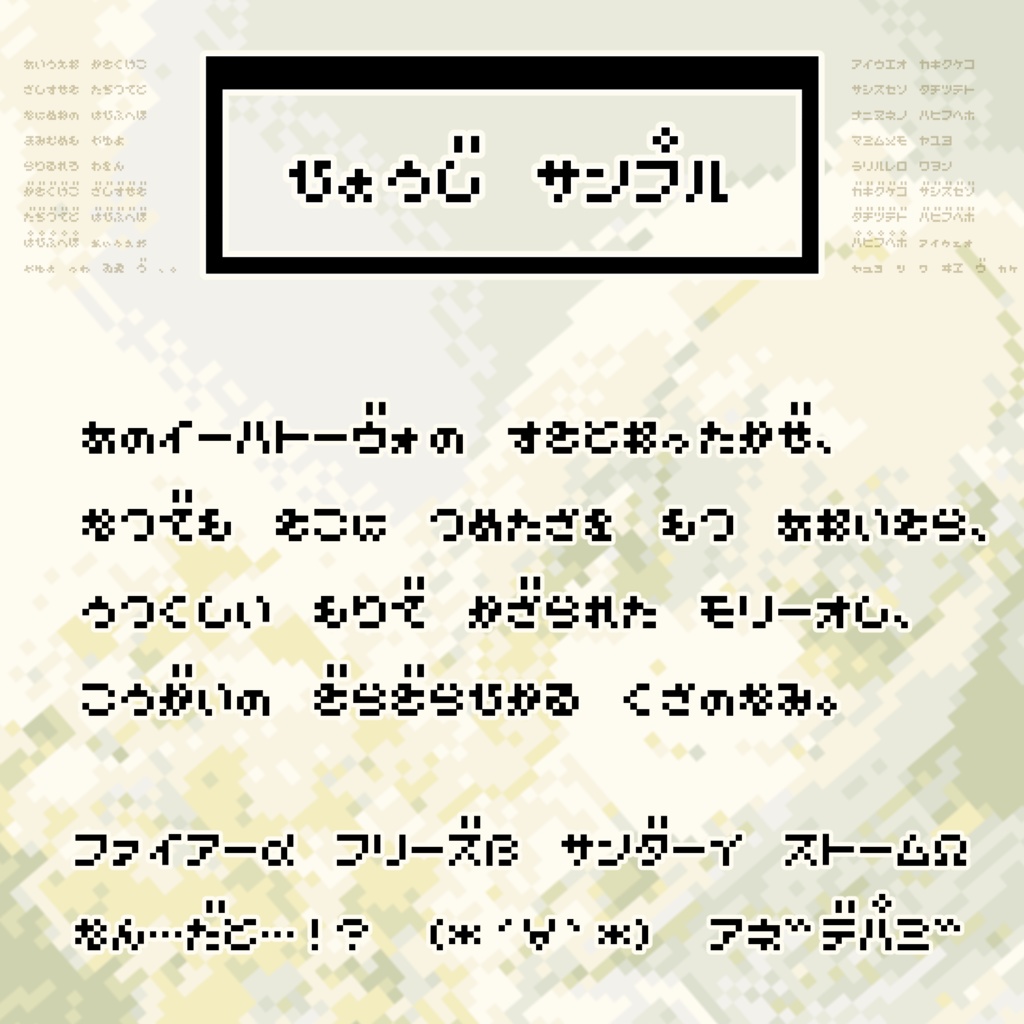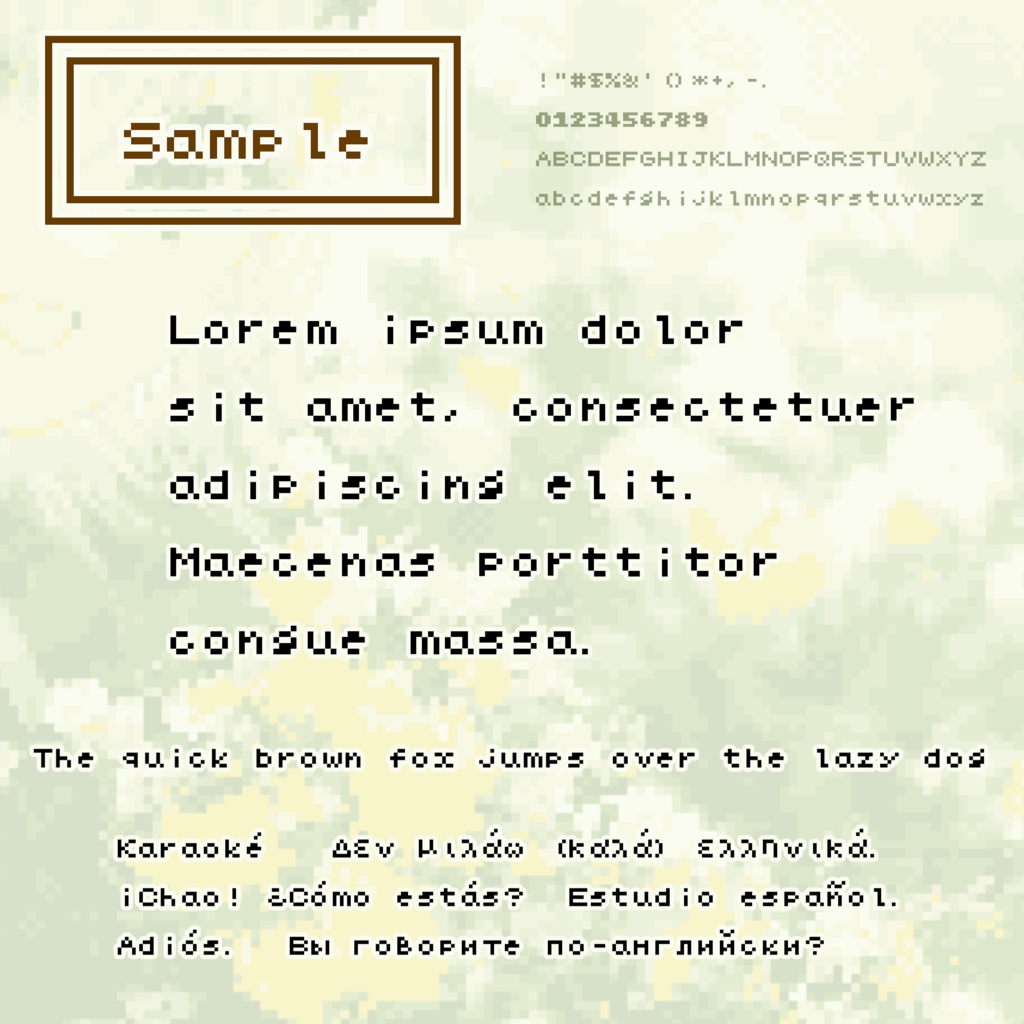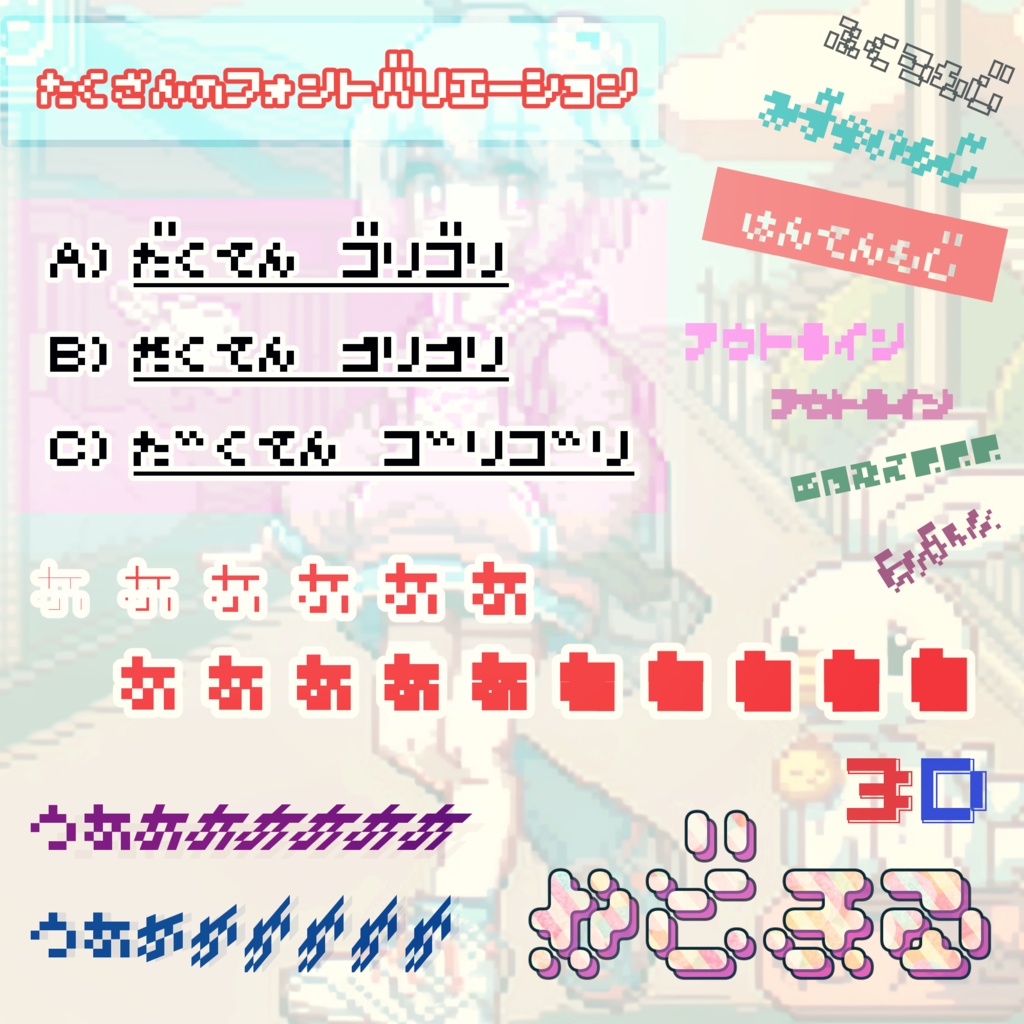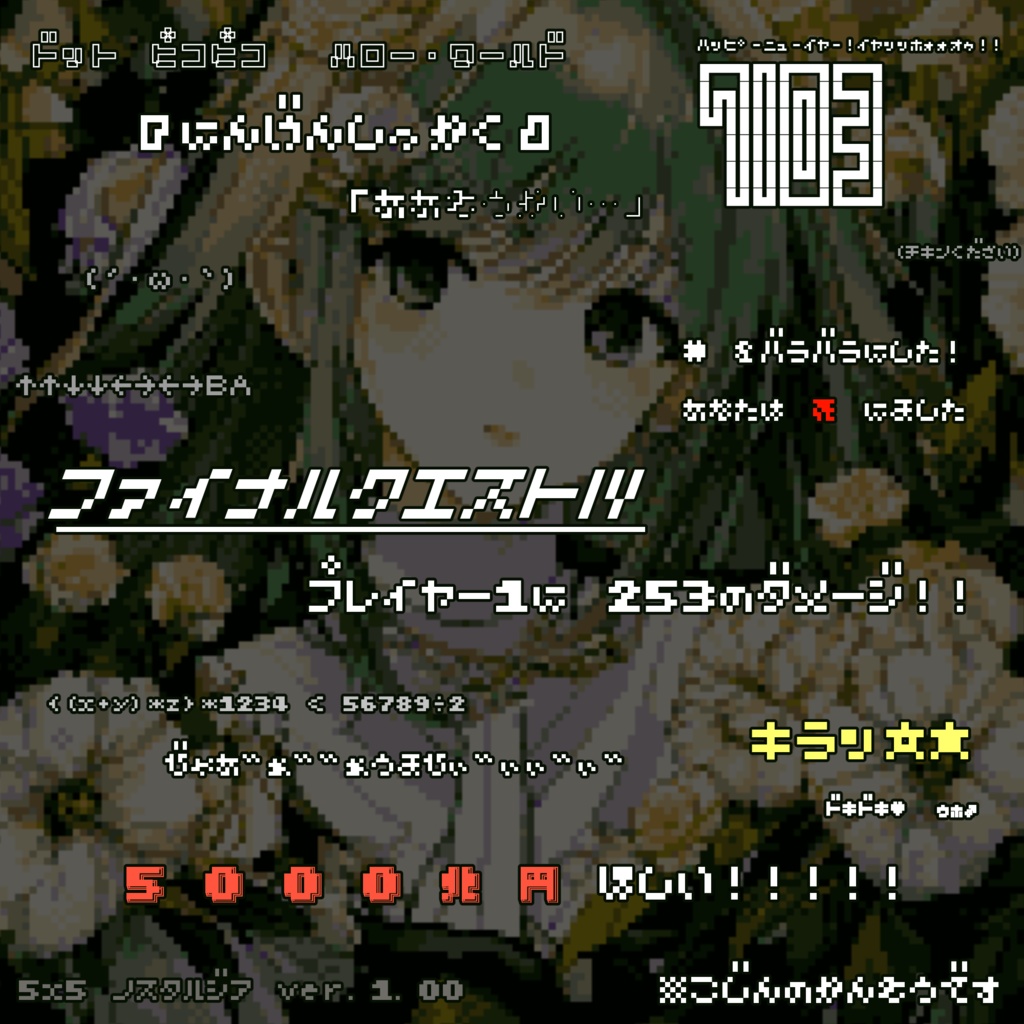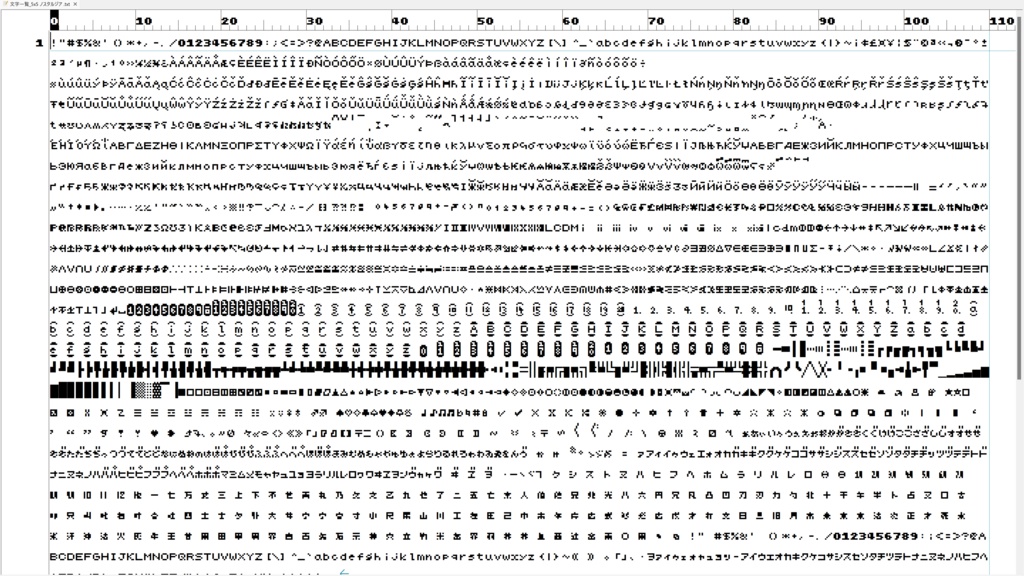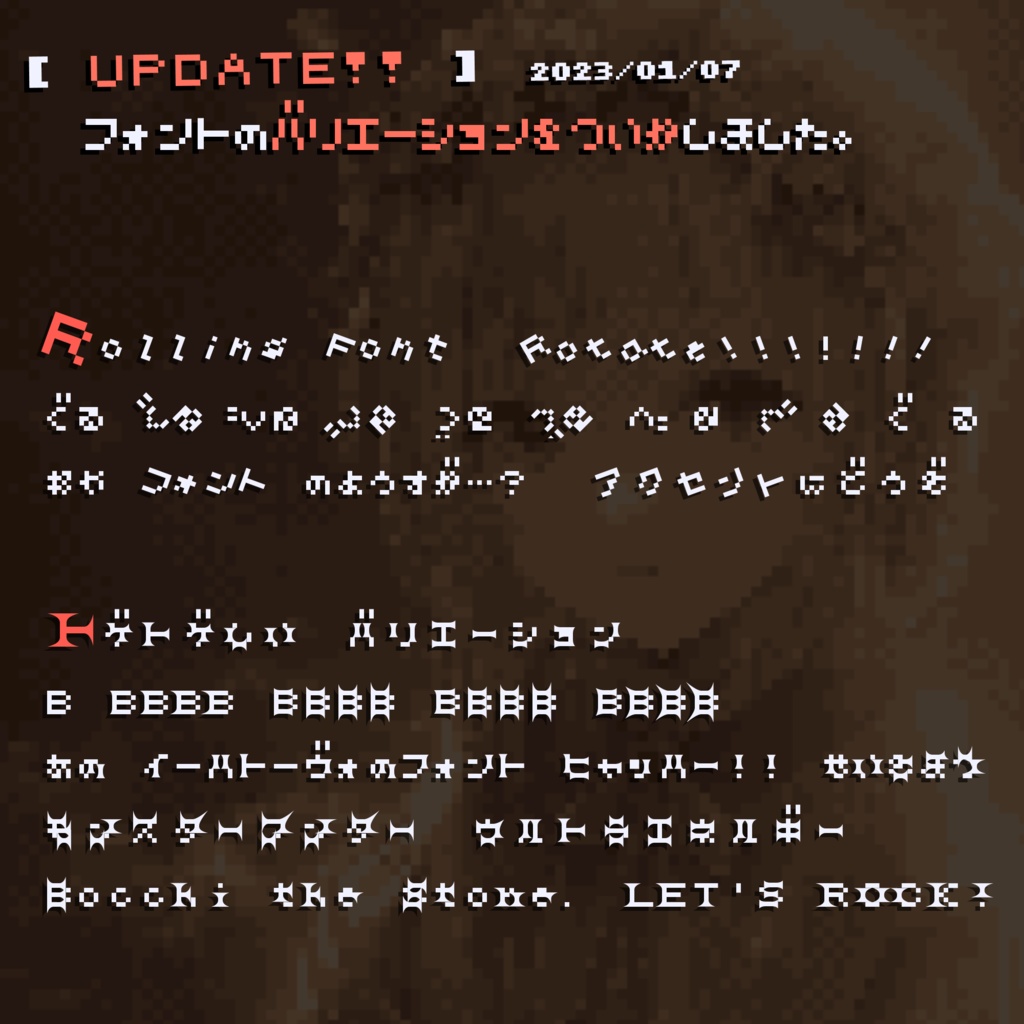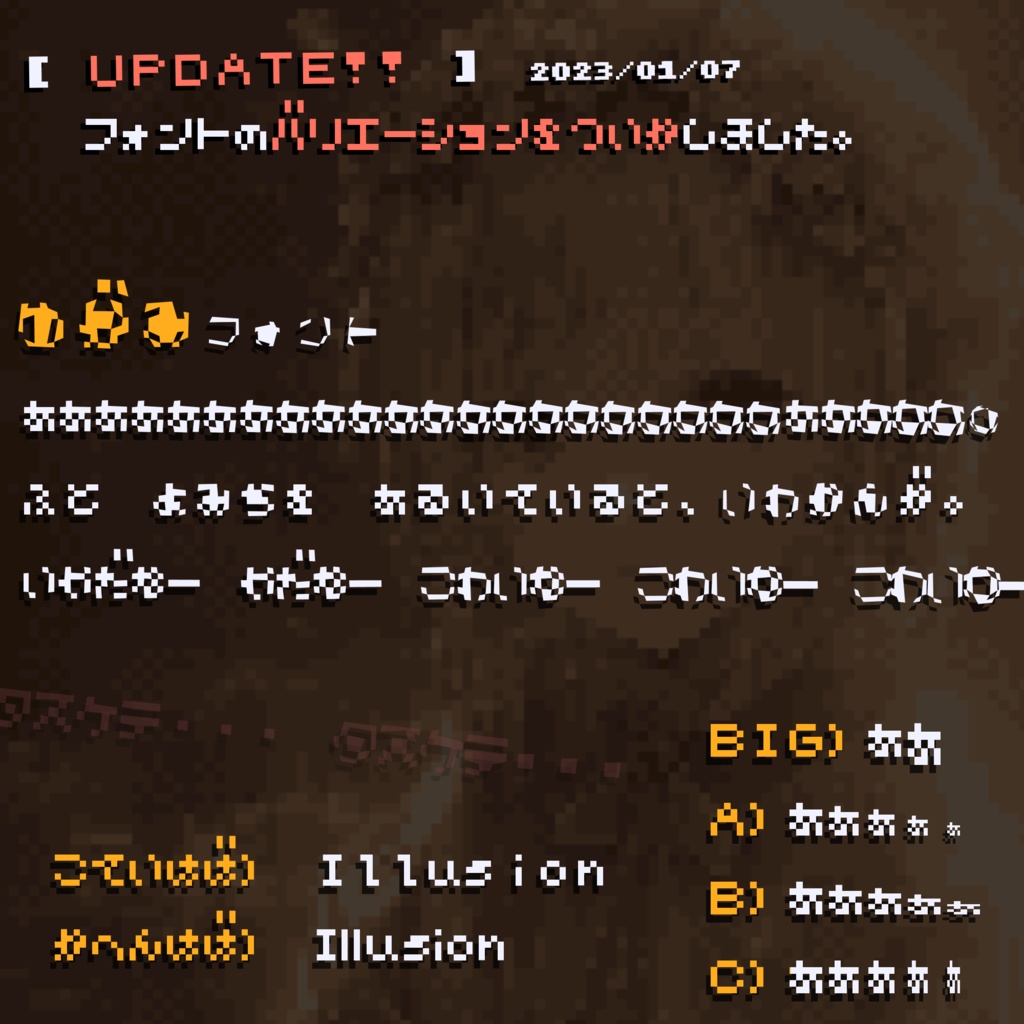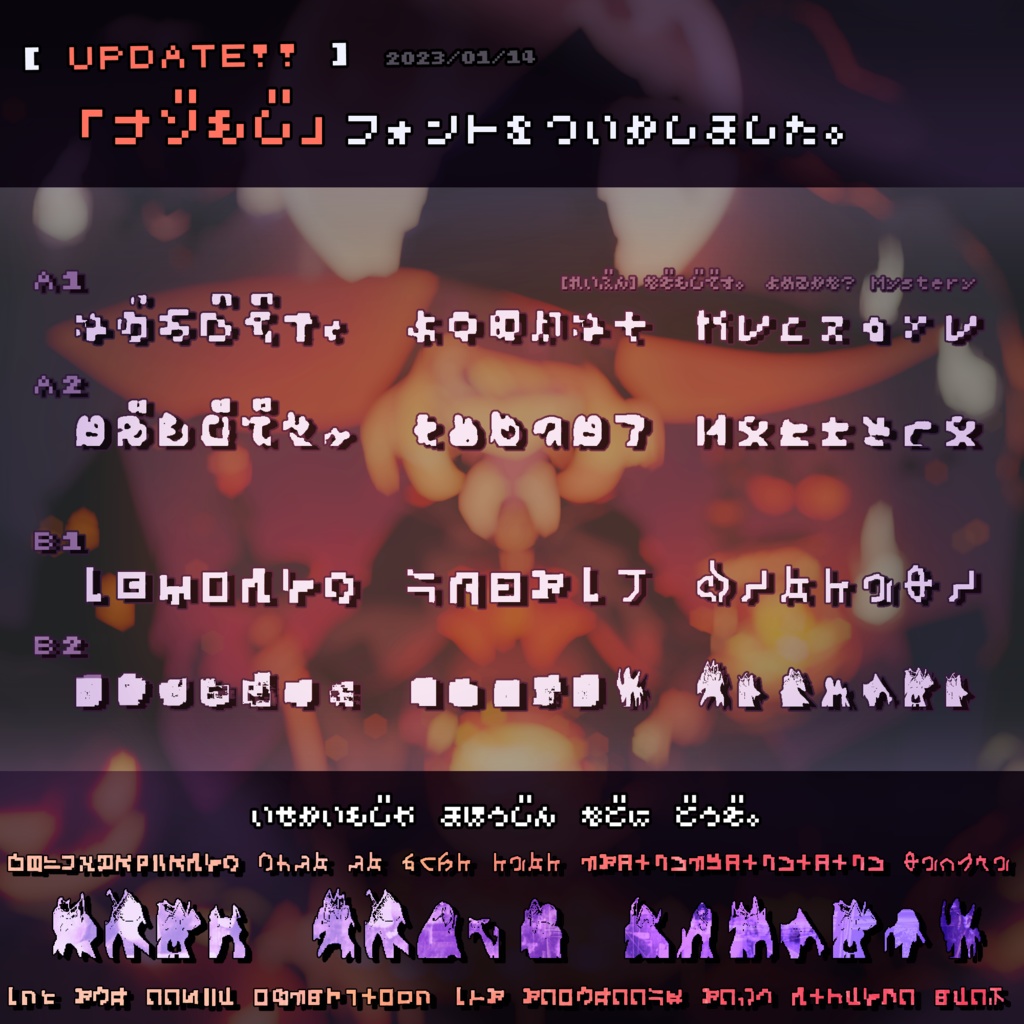
5×5サイズのピクセル風フォント『5x5 ノスタルジア』(5x5 Nostalgia)です。 小さな空間を大きく使ったデザイン。気の抜けた、柔らかい印象が特徴的。 「#5x5ピクセルフォントチャレンジ」という素敵な企画に触発され、制作を行いました。 基本的な文字の字形は5×5サイズ、表示のための余白等を含めると6×12サイズで構成されています。 ライセンス(利用規約) は「(旧)M+ FONT LICENCE」と同様の とても自由なライセンスとなります。 ゲーム等への組み込み使用、Webフォント化、改変、再配布等、 煮るなり焼くなりご自由にどうぞ。 もしお気に召しましたら、ご支援(Donate)をいただけますと非常に嬉しいです。 また、当フォントの紹介やご使用報告等をいただけますと飛び上がって喜びます👍
フォント バリエーション紹介
実験的なフォントを含め、非常にたくさんのフォントバリエーションがあります。 おすすめフォント → ★ 【基本フォント】 ★★★「5x5 ノスタルジア」(5x5 Nostalgia) バリエーションフォントの元となるメインバージョンです。迷ったらこれだけでもOK。 全2398文字。 ★★「Alt」 複数のフォント編集ソフトを跨いだ際にデータが失われてしまった「キリル文字補助」や「記号類」等の文字情報が残っているバージョンです。漢字未収録。フォントの構成情報がメインバージョンとは異なるため、使用ソフトによってはメインバージョンと表示結果が異なる可能性があります。 全4020文字。 ・「点入」(TEN in) ★「点外」(TEN out) 濁点・半濁点が付く「ひらがな・カタカナ」の一部字形が異なるバージョンです。 点中:5x5ピクセル内に収まるように字形を変更。 点外:「か゛」「は゜」のように文字の横に自動で点が付くような形になり、当該文字の文字幅は二倍に。レトロゲーム風の表示に便利です。 【バリエーション】 ソフトによる一括処理でフォントデータに加工を施し作成したフォントです。 加工処理によりフォントの文字枠外にはみ出た部分は、使用ソフトによってはうまく表示されない可能性があります。 ・「Alt - 〇〇」 フォント化前のデータに加工を加えてから作成した、実験的なバリエーションフォントです。 バグ風や乱視風、ゾンビ風など、総じて可読性が低いため、演出用途等に。 フォントの仕様は「Alt」と同様になります。 ★「角丸」(Round) ドットの角が丸くなったバージョンです。 大きなサイズでの表示で映える、ゆるくポップな印象に。 ・「細1~9」(Thin) フォントのアウトラインを細字化したバージョンです。 ・「斜体 横1~3」(Italic H) 全体に左右の斜体変形を施したバージョンです。 ・「斜体 縦1~3」(Italic V) 全体に上下の斜体変形を施したバージョンです。 ★★「太1~9」(Bold) フォントのアウトラインを太字化したバージョンです。 ドット表現と相性が良く実用性の高い、特にオススメのバージョンです。 ・「袋文字」(Outline) 全体に袋文字化を施したバージョンです。 ・「白黒反転」(Inversion) 全体に白抜き処理を施し、表示を反転させたバージョンです。 ★「立体1~5」(3D) 立体的な効果を加えたバージョンです。 表示サイズによっては「にじみ」のような表現にも。 ・「Misc」フォルダ ファイル数が多い、差異が小さい、ファイルサイズが大きい、といった理由で別枠としたフォントです。 ※「没フォント」フォルダから名称を変更しました。 【Update】 2023.01.07 以下のフォントバリエーションを収録した「Update 1」フォルダを追加しました。 ・「可変幅」(Proportional) 一部アルファベットの文字幅を調整した、可変幅フォントです。 ・「size 〇〇」 字形のサイズ、縦横比を変化させたバリエーションです。 フォント表示の字間や縦横比を調整できないソフト上での使用に適しています。 ★「回転」(Rotate) 字形を指定角度回転させたバリエーションです。 オススメ → 「回転C-〇〇」 ★「角立ち」(Shape) 縦線または横線の角を立たせた、トゲトゲした形のバリエーションです。 オススメ → 「角立て 2x0、0x2、2x2」 ・「歪み」(Deform) 回転処理により生じる誤差により、意図的に字形を歪ませたフォントです。 オススメ → 「歪みA5、A10、A15、A20」 【Update】 2023/01/14 以下のフォントバリエーションを収録した「Update 2」フォルダを追加しました。 ・「ナゾ文字 〇〇」(???) AIを用いた加工によって生まれた、謎の文字風フォントです。 印字のにじみ、異世界文字、魔法陣といった演出用途にどうぞ。 ※収録文字:「半角英数字」「ひらがな」「カタカナ」